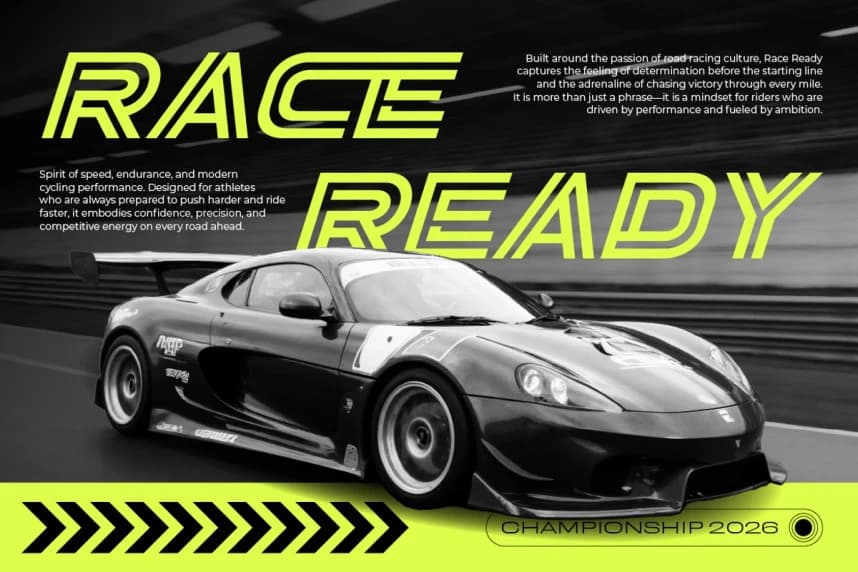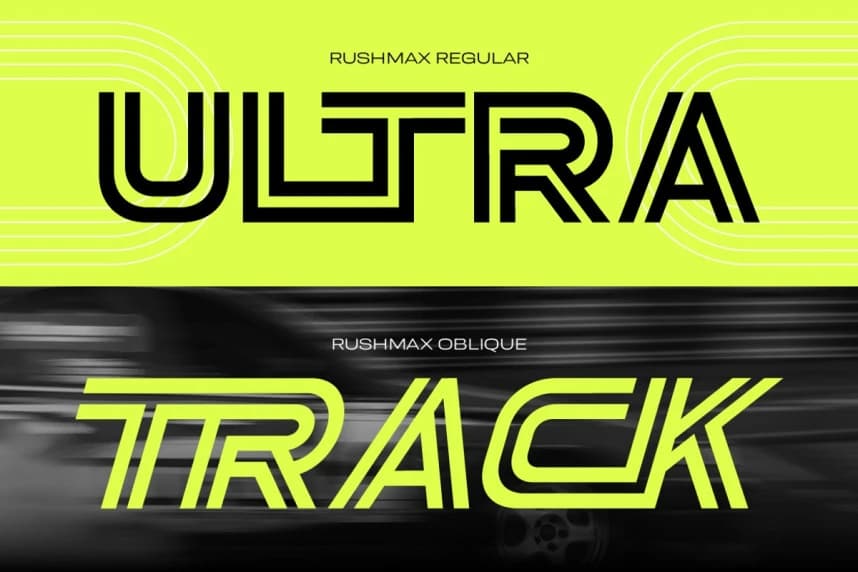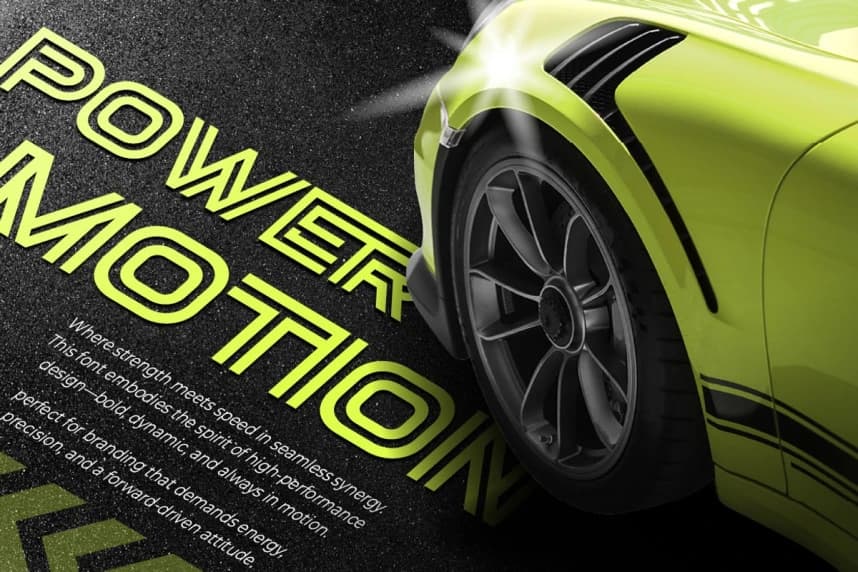
Rushmax Yazı Tipi İndir
Rushmax Font, her harfinde hız, güç ve geleceğe yönelik enerji yakalamak üzere tasarlanmış cesur bir modern spor yazı tipidir. Keskin çizgiler, dinamik eğriler ve yüksek performans estetiği ile tasarlandı. Bu yazı tipi, güçlü ve agresif bir görsel etki talep eden projeler için mükemmeldir.
Rushmax Font, her harfte hız, güç ve fütüristik enerji yakalamak için tasarlanmış kalın ve modern bir spor yazı tipidir. Keskin hatlar, dinamik eğriler ve yüksek performans estetiği ile tasarlanmış bu yazı tipi, güçlü ve agresif bir görsel etki gerektiren projeler için mükemmeldir.